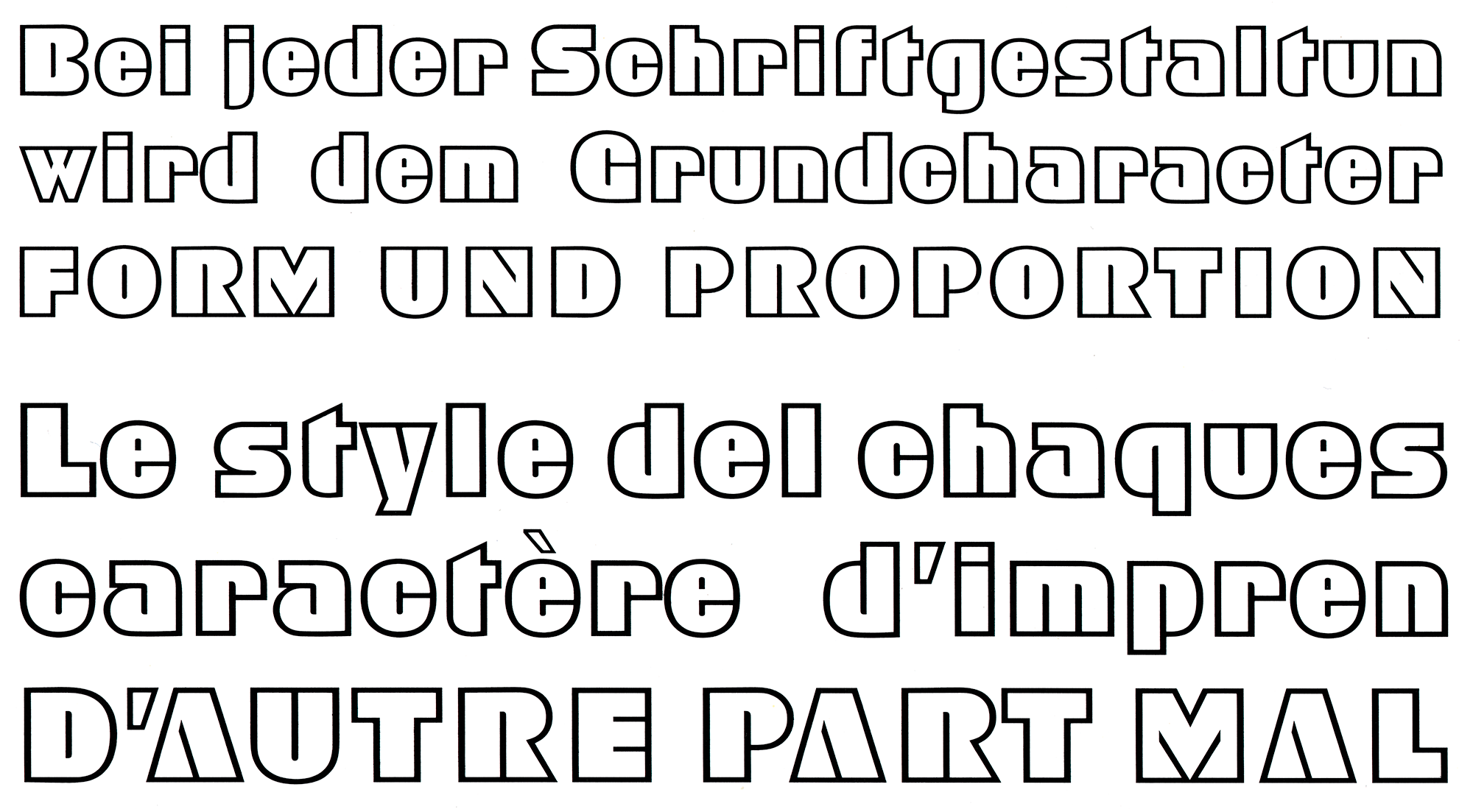
Die Bloc ist eine lichte, fette Schaugrößenschrift von Aldo Novarese, die in den 1970er-Jahren als Fotosatzschrift über die Visual Graphics Corporation und Linotype erschien.